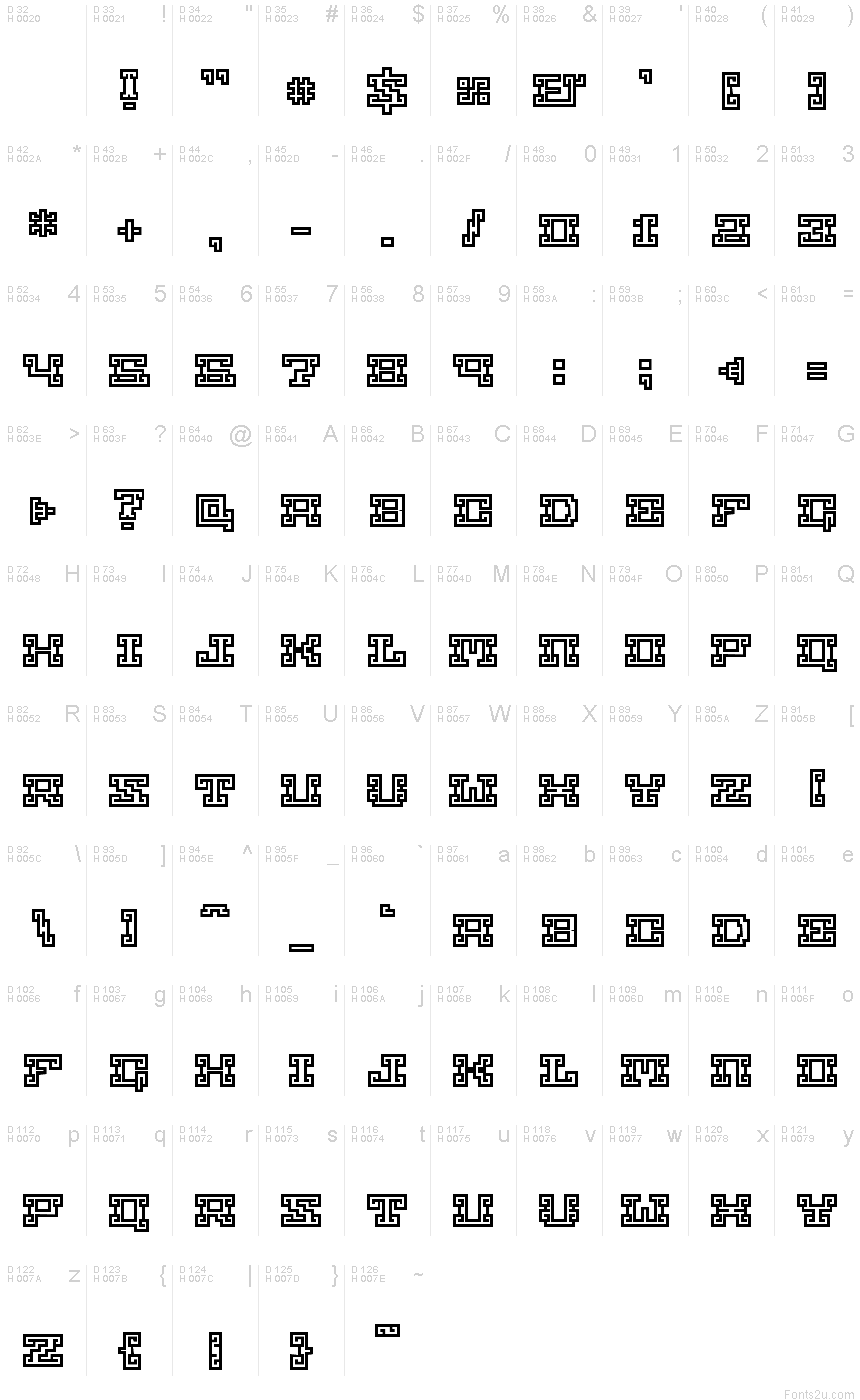
Maja von Miguel Hernandez ist eine kostenlose mexikanische Display-Schrift mit einem markanten, labyrinthartigen Rhythmus. Die Buchstaben verwandeln blockartige Striche in abgestufte Ecken und gewundene quadratische Spiralen, was den Großbuchstaben einen handgemalten Wandgemälde-Look verleiht – mit einem Hauch von Volkskunst statt kühler Geometrie.
Sie eignet sich perfekt für Plakate, Festival-Grafiken, Plattencover, Restaurant-Branding und Titel, bei denen ein kurzes Wort das Muster tragen kann. Als kostenlose Schrift funktioniert MAJA auch hervorragend für Monogramme oder Titelzeilen, da die sich wiederholenden Mäanderformen selbst wenige Buchstaben wie einen vollständigen Rahmen samt Überschrift wirken lassen.